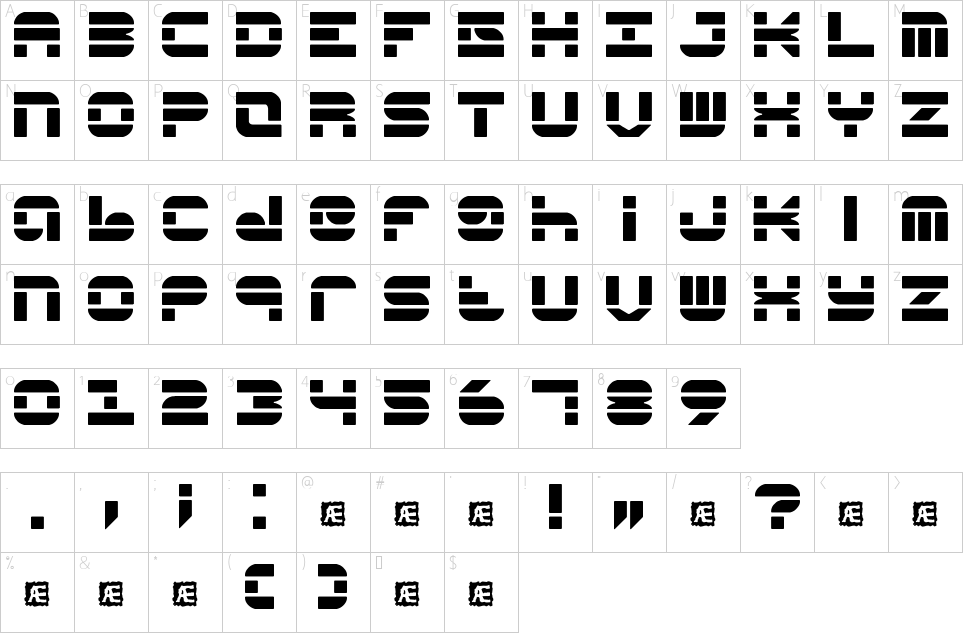
A Pseudo Font é uma criação de Aenigma Fonts, uma fonte única e intrigante que se destaca em qualquer projeto visual. Inspirada em desenhos abstractos e emaranhados, essa fonte oferece uma maneira original de dar uma nova dimensão à sua tipografia. Ela foi projetada para Windows e Mac e já foi baixada mais de duas mil vezes, provando seu valor e interesse para designers de todo o mundo. Se você está procurando por uma fonte que se destaque e ofereça um toque inovador ao seu trabalho, a Pseudo Font é uma escolha excelente.